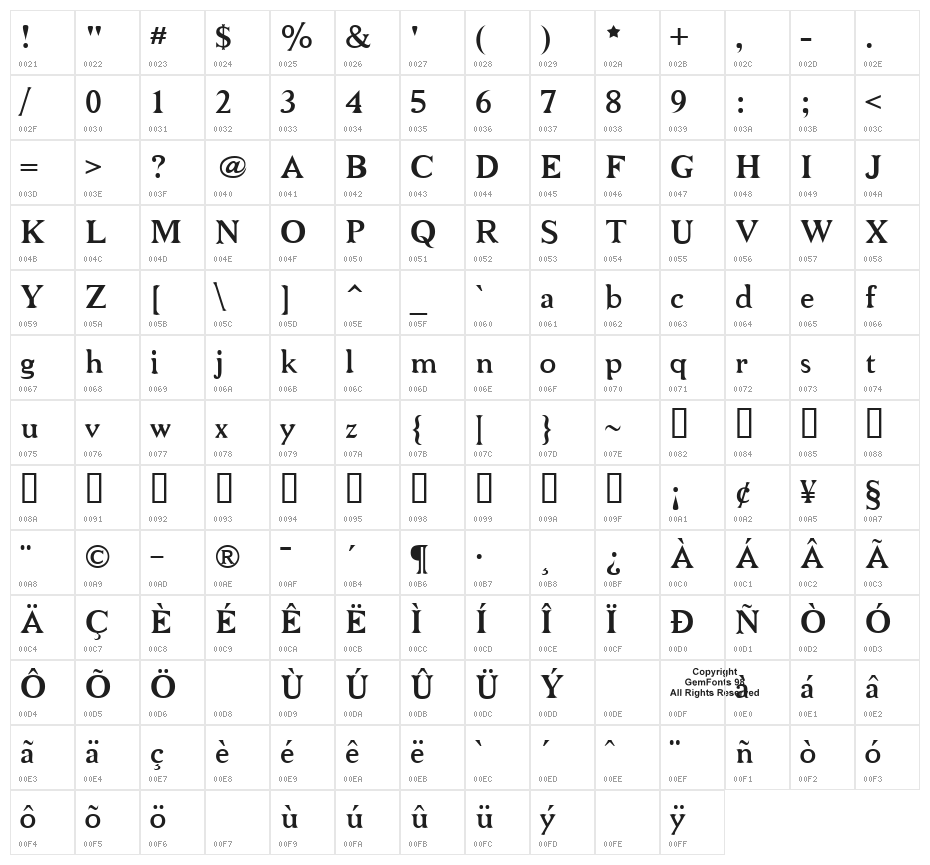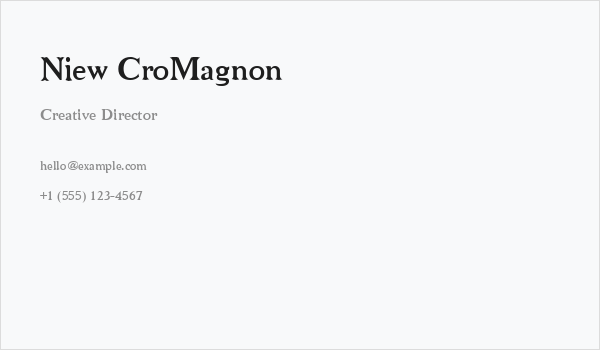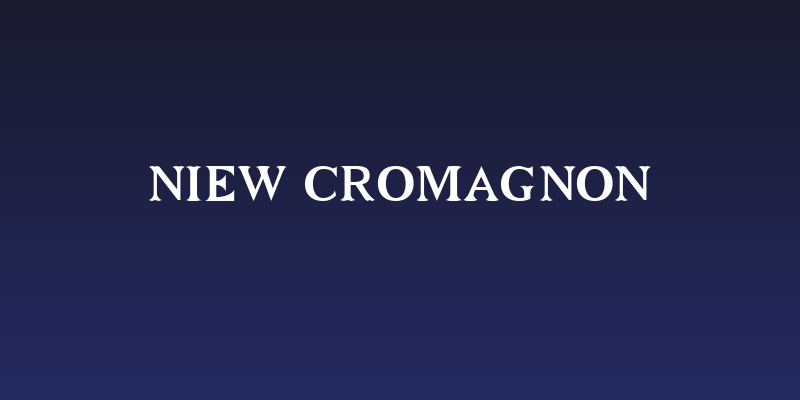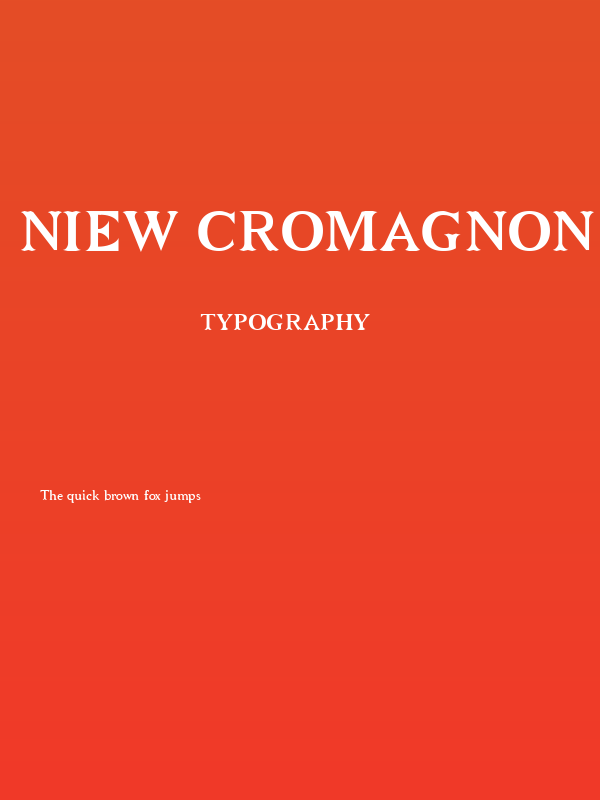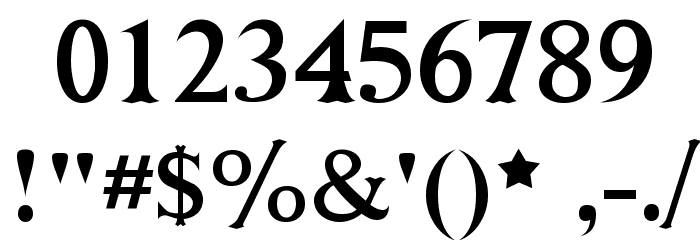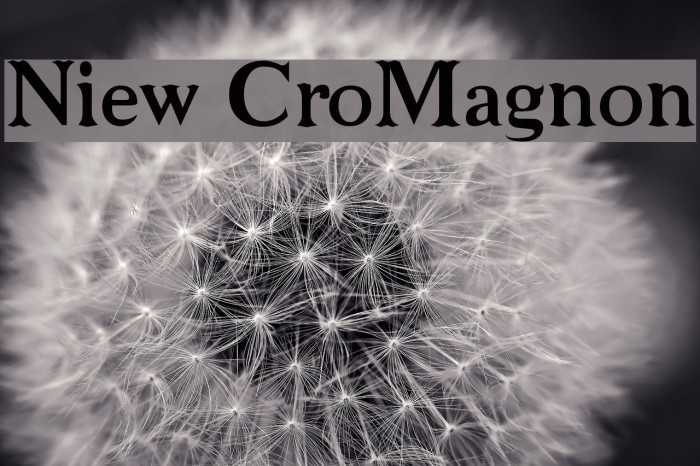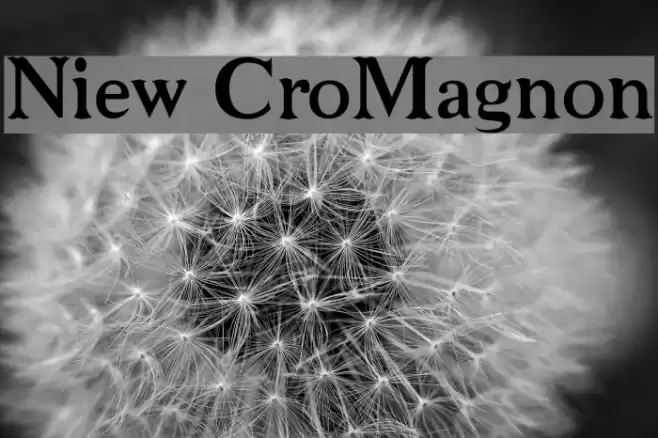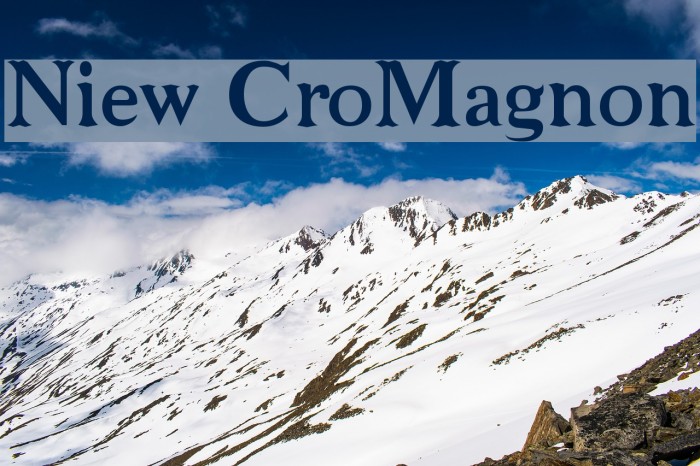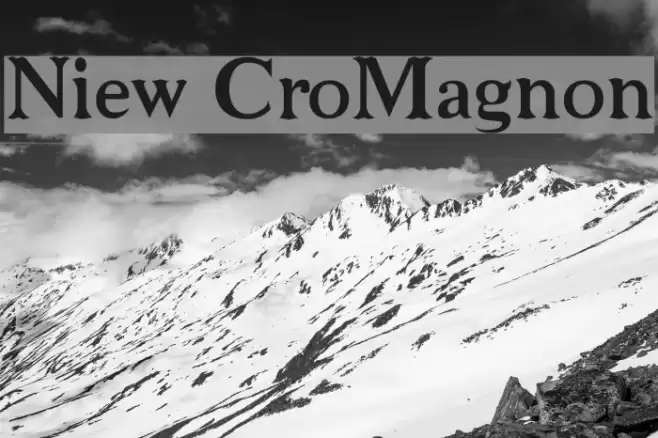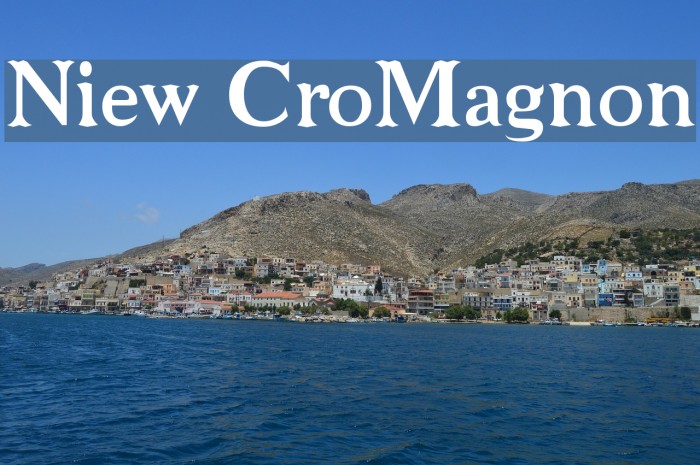
Niew CroMagnon Font
✎ Formal
| Categorie | Formal |
| Caso d'uso | Headlines, Book covers, Posters, Branding |
| Progetti proposti | Ideal for use in headlines, book covers, posters, and branding materials that require a strong and elegant serif typeface. |